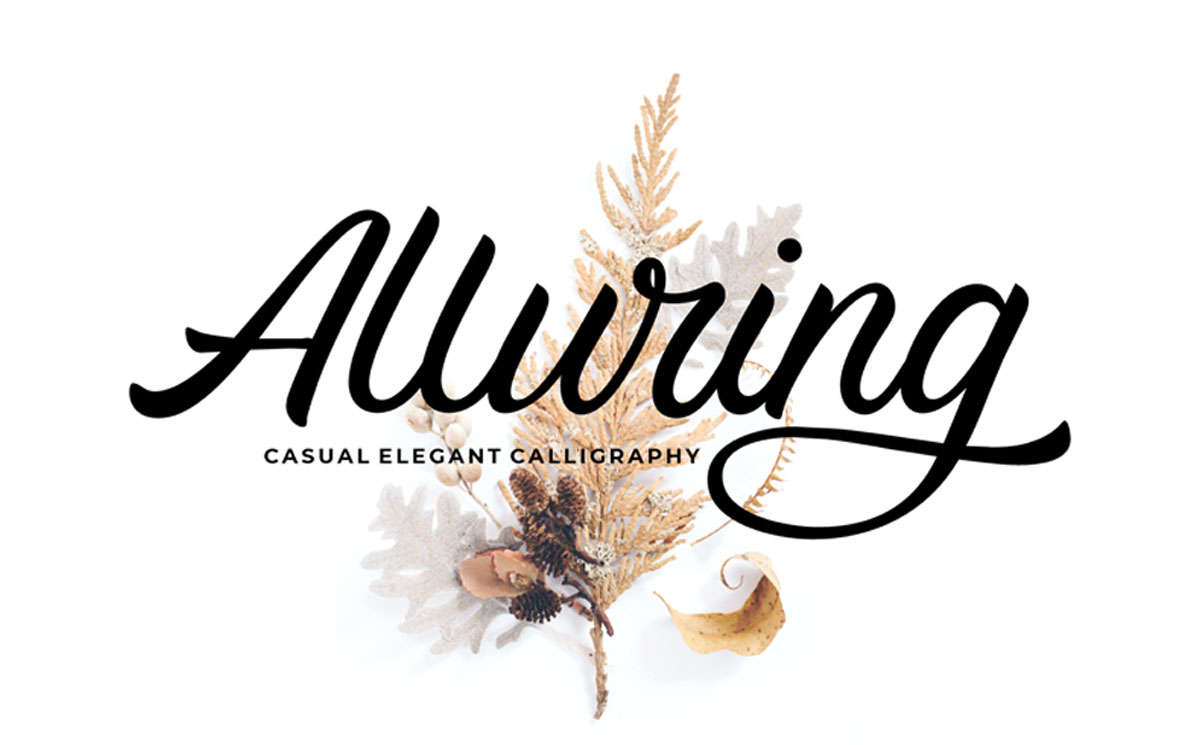
Trong thế giới thiết kế đồ họa, việc lựa chọn đúng font chữ có thể quyết định sự thành bại của cả một tác phẩm. Nếu bạn đang tìm kiếm một phông chữ mang đậm nét thanh lịch, lãng mạn và mềm mại, thì font chữ viết tay SVN Alluring chính là “chân ái”.
1. Giới thiệu về Font chữ viết tay SVN Alluring
SVN Alluring là một phông chữ thuộc dòng Script (chữ viết tay) được giới thiết kế vô cùng ưa chuộng. Nguyên bản của font chữ này mang đậm phong cách calligraphy hiện đại, với những đường nét bay bổng, uyển chuyển như được viết ra từ một chiếc bút mực điêu luyện.
Đặc biệt, tiền tố “SVN” cho biết đây là phiên bản đã được Việt hóa hoàn chỉnh. Điều này đồng nghĩa với việc bạn có thể thoải mái gõ tiếng Việt có dấu mà không lo bị lỗi font hay lệch dấu – một vấn đề thường gặp khi sử dụng các phông chữ nước ngoài.
2. Đặc điểm nổi bật của phông chữ SVN Alluring
Không phải ngẫu nhiên mà SVN Alluring lại lọt top những phông chữ miễn phí được săn đón nhất. Dưới đây là những ưu điểm vượt trội của font chữ này:
Đường nét tinh tế, sang trọng: Các con chữ được thiết kế với độ thanh đậm rõ ràng, tạo cảm giác tự nhiên, mượt mà nhưng không kém phần sang trọng.
Hỗ trợ tiếng Việt 100%: Được việt hóa chỉn chu, bộ dấu được đặt tinh tế, hài hòa với tổng thể của từng chữ cái.
Đa dạng ký tự thay thế (Alternates & Ligatures): Font cung cấp nhiều nét gạch nối và ký tự cách điệu ở đầu hoặc cuối chữ, giúp người dùng tự do sáng tạo typography mang đậm dấu ấn cá nhân.
3. Ứng dụng của font SVN Alluring trong thiết kế
Với sự linh hoạt và vẻ đẹp lãng mạn, SVN Alluring có thể “cân” được rất nhiều ấn phẩm thiết kế khác nhau:
| Lĩnh vực ứng dụng | Gợi ý thiết kế |
| Thiệp cưới & Sự kiện | Thiệp mời, bảng tên cô dâu chú rể, menu tiệc cưới, chữ hỷ cách điệu. |
| Nhận diện thương hiệu | Thiết kế Logo cho các spa, tiệm nail, cửa hàng hoa, thương hiệu thời trang nữ hoặc mỹ phẩm. |
| Truyền thông & Mạng xã hội | Làm font chữ chủ đạo cho các bức ảnh Quote (trích dẫn) tình yêu, cuộc sống trên Facebook, Instagram. |
| Bao bì sản phẩm | Nhãn mác các sản phẩm handmade, nến thơm, trà hoa, mang lại cảm giác thân thiện và cao cấp. |
Mẹo thiết kế (Design Tip): Để ấn phẩm không bị rối mắt, hãy kết hợp font viết tay SVN Alluring (làm điểm nhấn, tiêu đề) với một font chữ Sans-serif (không chân) hoặc Serif (có chân) cơ bản để trình bày nội dung văn bản (body text).